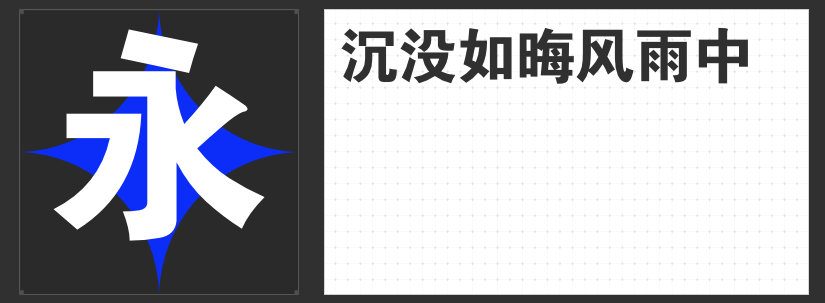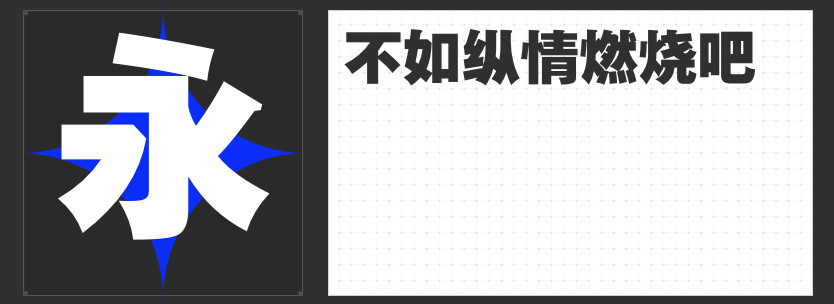
四款力量感字库推荐:重塑包装设计的视觉骨架
在商品同质化严重的今天,包装设计的字体选择已成为品牌突围的关键。一款兼具力量感与美感的标题字体,既能瞬间抓住消费者视线,又能传递品牌的核心气质。本文精选四款专为包装设计打造的精品字库,它们以无衬线设计的现代美学为基础,通过笔画的粗细变化与结构重构,为产品赋予独特的视觉张力。
一、励字勇敢黑简 大黑
这款字体以极简的无衬线设计打破传统标题字的繁复感,笔划粗壮如钢筋铁骨,撇捺收笔处采用钝角处理,既保证远距离的识别度,又避免尖锐笔画带来的攻击性。横竖笔画的均匀分布形成稳定的视觉重心,特别适合作为包装主标题或品牌标识的核心元素,能在货架陈列中迅速建立存在感。
二、励字综艺简繁
通过加粗笔画与圆润拐角的创新组合,这款字体在力量感与亲和力间找到完美平衡。设计师巧妙压缩笔画间距,使字形呈现饱满的块状结构,同时对转折处进行微弧处理,既保持无衬线字体的现代感,又增添一丝灵动气质。其繁简双版本设计,更可满足不同市场区域的包装需求,是高端消费品包装的优选方案。
三、励字励黑简
源自出版领域的经典标题字设计,这款字体将超粗笔画与正方形字面相结合,创造出如印章般的稳重感。方头起笔与无字肩折笔的设计,强化了字体的机械美学,而笔画粗细的绝对统一,则确保了小字号下的清晰可读性。无论是作为包装副标题还是重点信息提示,都能形成强烈的视觉层次。
四、励字粗黑简繁
作为无衬线字体的集大成者,这款字体以绝对均匀的笔画粗细构建出不可撼动的视觉权威。横平竖直的结构框架暗含东方美学精髓,而端庄的字形轮廓又赋予其国际化的现代气质。繁简双版的设置,使其既能适应传统市场的审美需求,又能契合年轻消费群体的极简偏好。
这四款字体通过笔画粗细、结构比例与细节处理的差异化设计,为包装设计提供了丰富的视觉语言选择。它们如同精心打磨的视觉工具,助力品牌在方寸之间构建独特的记忆点。